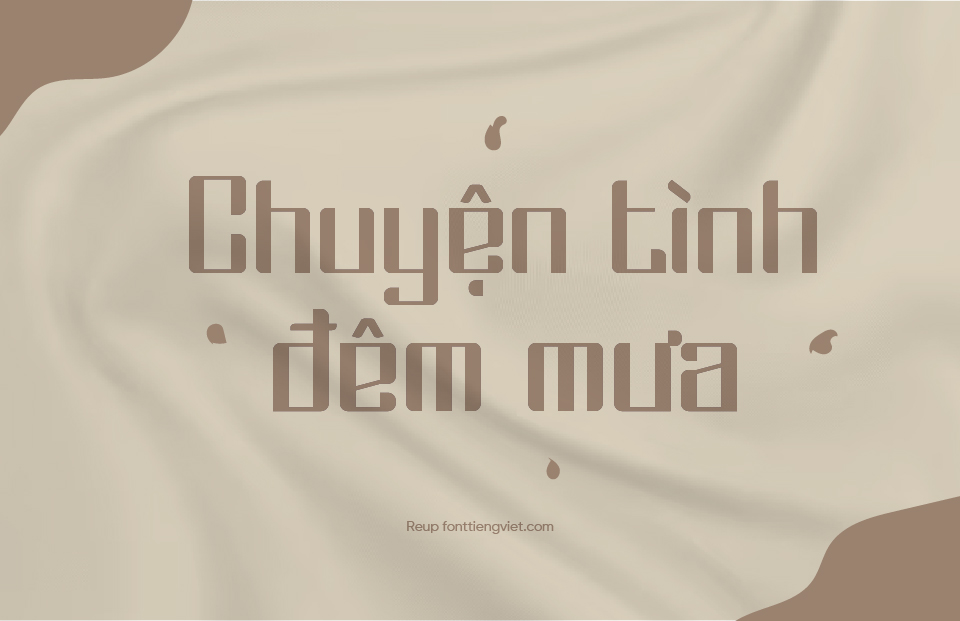
Font Việt hóa SVN Crosver
Khám phá sức hút từ bộ Font Việt hóa SVN Crosver chuyên nghiệp
Giới thiệu về Font Việt hóa SVN Crosver trong thiết kế
Trong thế giới sáng tạo, việc tìm kiếm một bộ Font Miễn Phí chất lượng luôn là ưu tiên hàng đầu của các bạn học sinh và giáo viên. Font Việt hóa SVN Crosver nổi lên như một lựa chọn hoàn hảo nhờ sự kết hợp tinh tế giữa nét chữ hiện đại và khả năng hiển thị tiếng Việt mượt mà. Đây là bộ phông chữ thuộc phong cách Sans Serif, mang đến cảm giác gọn gàng, thanh lịch nhưng không kém phần mạnh mẽ cho mọi bản thiết kế từ bài giảng điện tử đến báo tường trường học.
Những đặc điểm nổi bật của Font Việt hóa SVN Crosver
Thiết kế hiện đại và đa dạng ứng dụng
Font Việt hóa SVN Crosver được đánh giá cao bởi các đường nét được tối ưu hóa cho hiển thị kỹ thuật số. Với độ tương phản thấp và cấu trúc hình học chuẩn xác, bộ chữ này giúp người xem dễ dàng đọc nội dung ngay cả ở kích thước nhỏ. Điều này cực kỳ hữu ích khi các bạn áp dụng vào làm slide thuyết trình hoặc thiết kế sơ đồ tư duy trong học tập.
Khả năng tương thích và hỗ trợ tiếng Việt
Điểm cộng lớn nhất chính là bộ gõ tiếng Việt đã được tinh chỉnh hoàn thiện. Bạn sẽ không còn gặp lỗi dấu đè lên chữ hay khoảng cách ký tự không đều. Sự chỉn chu trong từng nét chữ giúp Font Việt hóa SVN Crosver trở nên chuyên nghiệp hơn bao giờ hết, phù hợp cho cả mục đích in ấn lẫn trình chiếu trên các thiết bị di động.